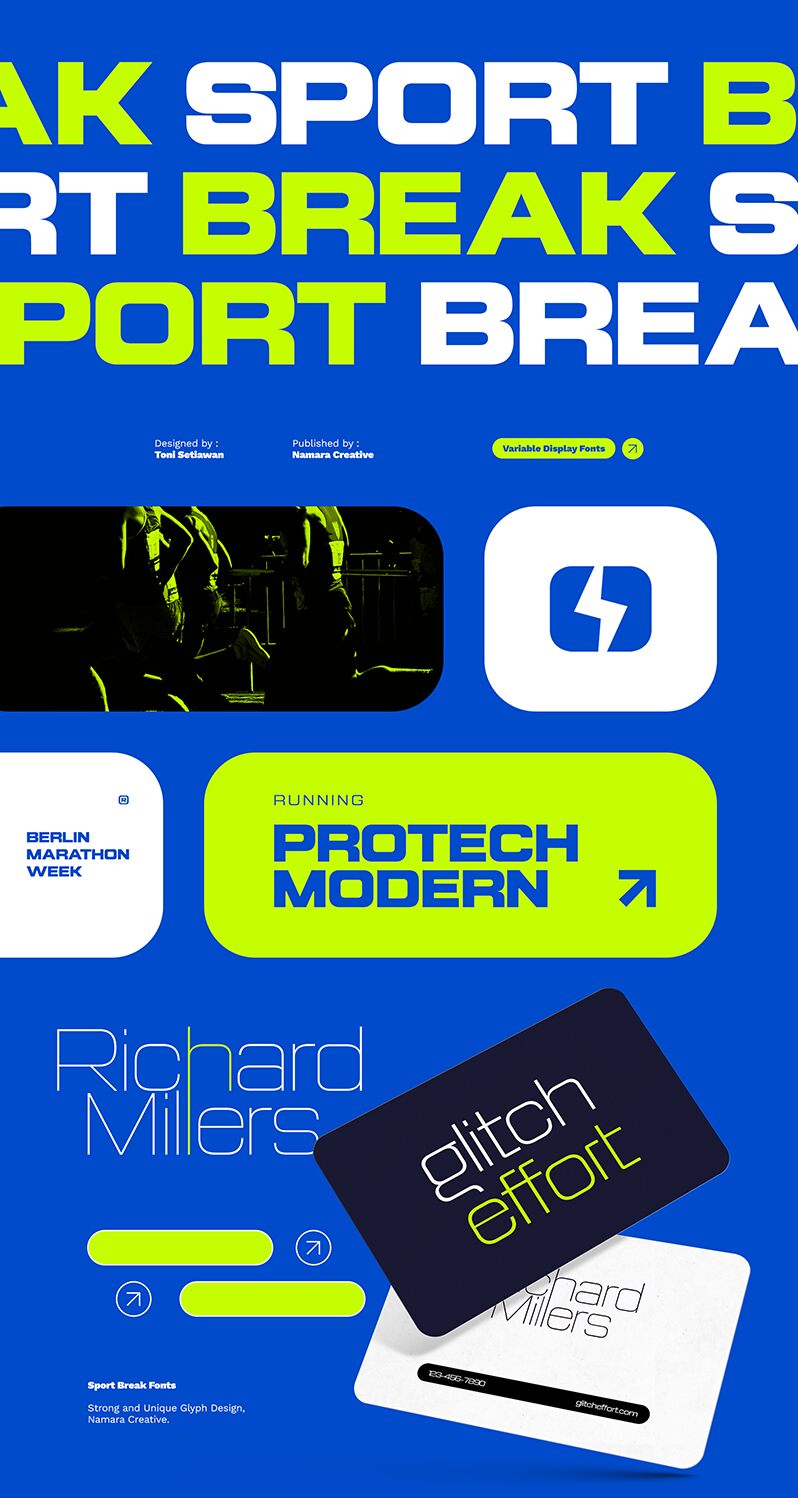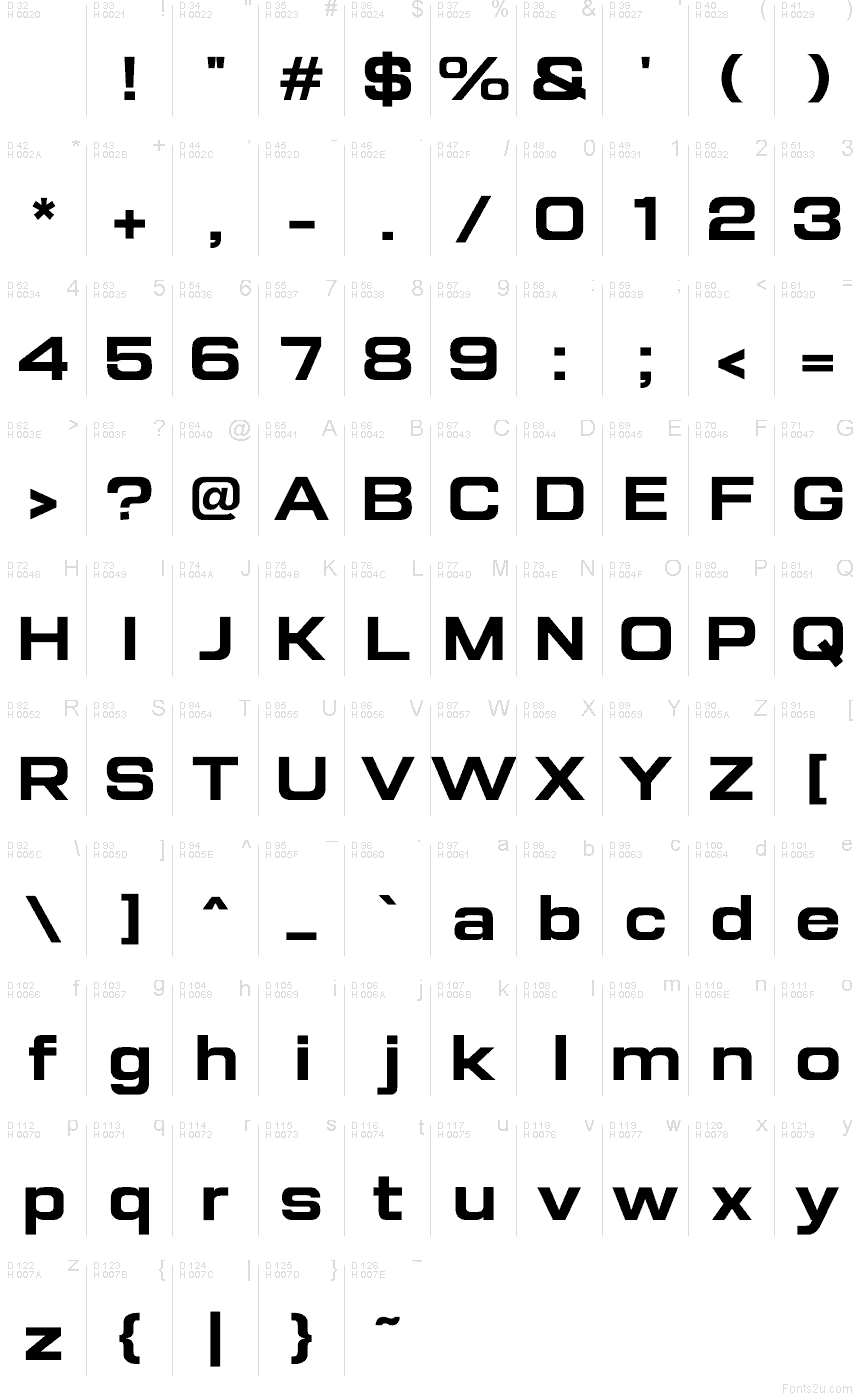
Sport Break Free Version
Sport Break من Namara Creative هو خط عرض مجاني ذو زوايا دائرية، يتميز بمنحنيات مستطيلة عريضة وصورة ظلية مدمجة. تبدو الحروف ككتل ناعمة ومضغوطة، مع زوايا مخففة تحافظ على طابع ودي للتصميم، بينما تمنح الأشكال المربعة الخط مظهرًا حيويًا ومباشرًا يشبه لافتات الإعلانات.
هذا المزيج مثالي للعلامات التجارية الرياضية، ولافتات الرياضات الإلكترونية، وملصقات النوادي الرياضية، وتصاميم الفرق، وعناوين التطبيقات التي تتطلب تأثيرًا بصريًا قويًا للكلمات القصيرة. وبفضل حجمه المدمج وهندسته الدائرية، يعد الخط مناسبًا أيضًا لتصاميم التغليف وعناوين الشاشات، خاصة عندما يتطلب المشروع طاقة حيوية دون الحواف الحادة والقاسية للخطوط التقنية العادية.